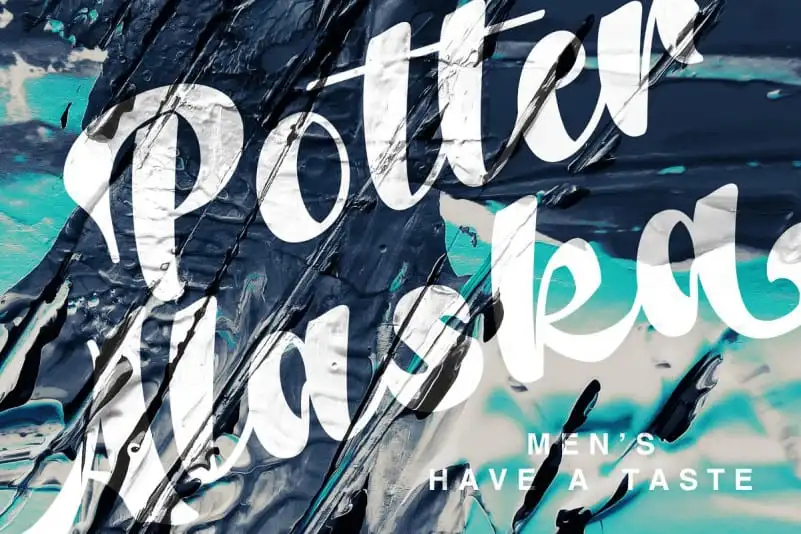
Potter Alaska Font – Download Grátis
A Potter Alaska Font é uma escolha perfeita para projetos que buscam um toque artístico forte e autêntico. Esta fonte elegante e quirk, criada pelo designer Aldedesign com a influência do estilo de escrita manuscrita, oferece uma abordagem versátil tanto para cartazes quanto para editoração profissional. Com sua presença chamativa e ligaturas detalhadas, ela é perfeita para criar textos que se destacam. A potencialidade da Potter Alaska Font vai muito além do simples estilo: com sua natureza dinâmica e fortes estilos, ela está pronta para tornar qualquer projeto de design mais criativo e interessante. Uma fonte poderosa e elegante como esta faz um excelente complemento aos teus projetos digitais. Não perca a oportunidade de dar vida à tua próxima criação visual com a Potter Alaska Font.